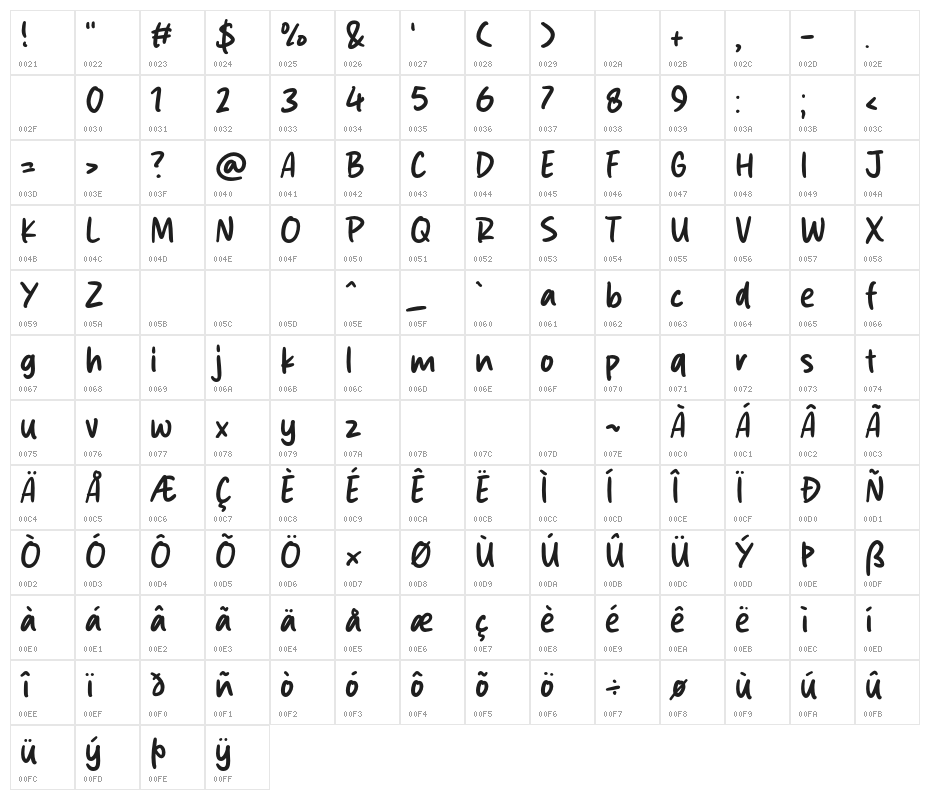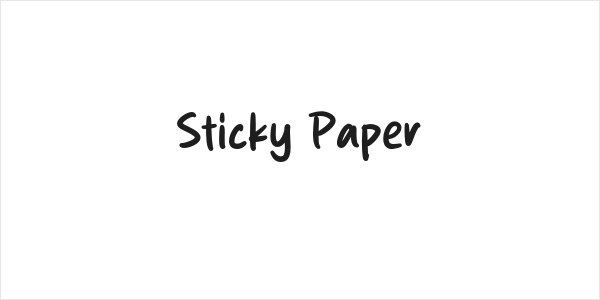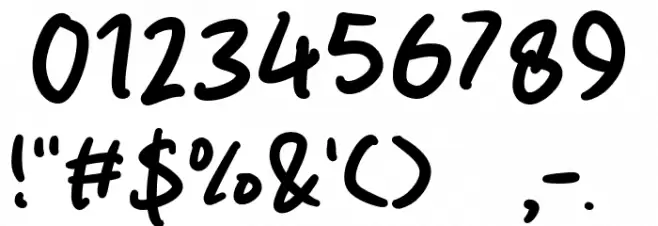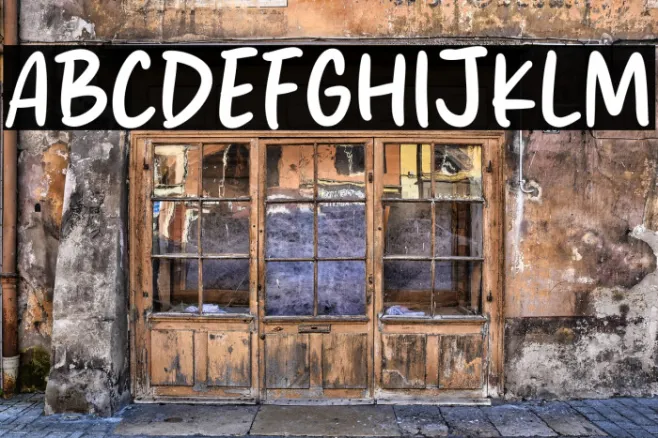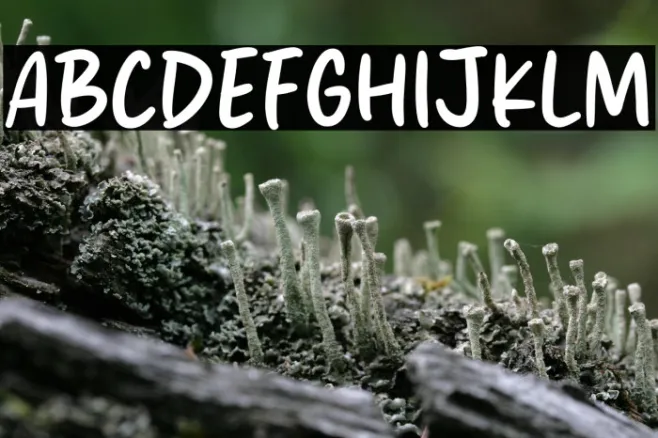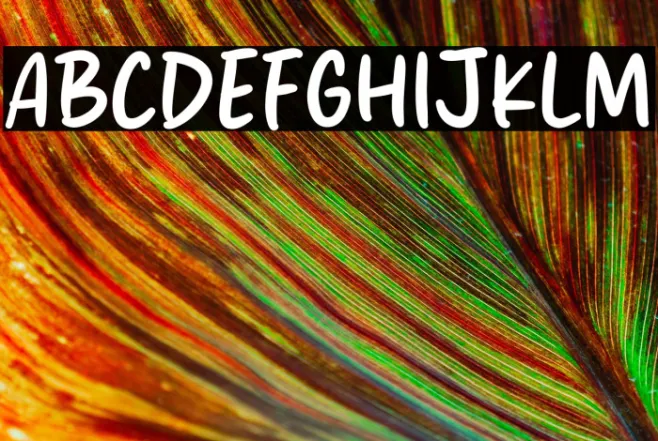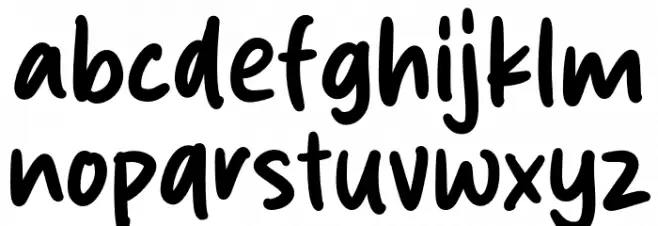
Sticky Paper Font
| Gesamtstil | Casual |
| Anwendungsfall | Logos, Headlines, Informal text |
| Vorgeschlagene Projekte | Ideal for greeting cards, children's books, playful branding, and social media graphics. |